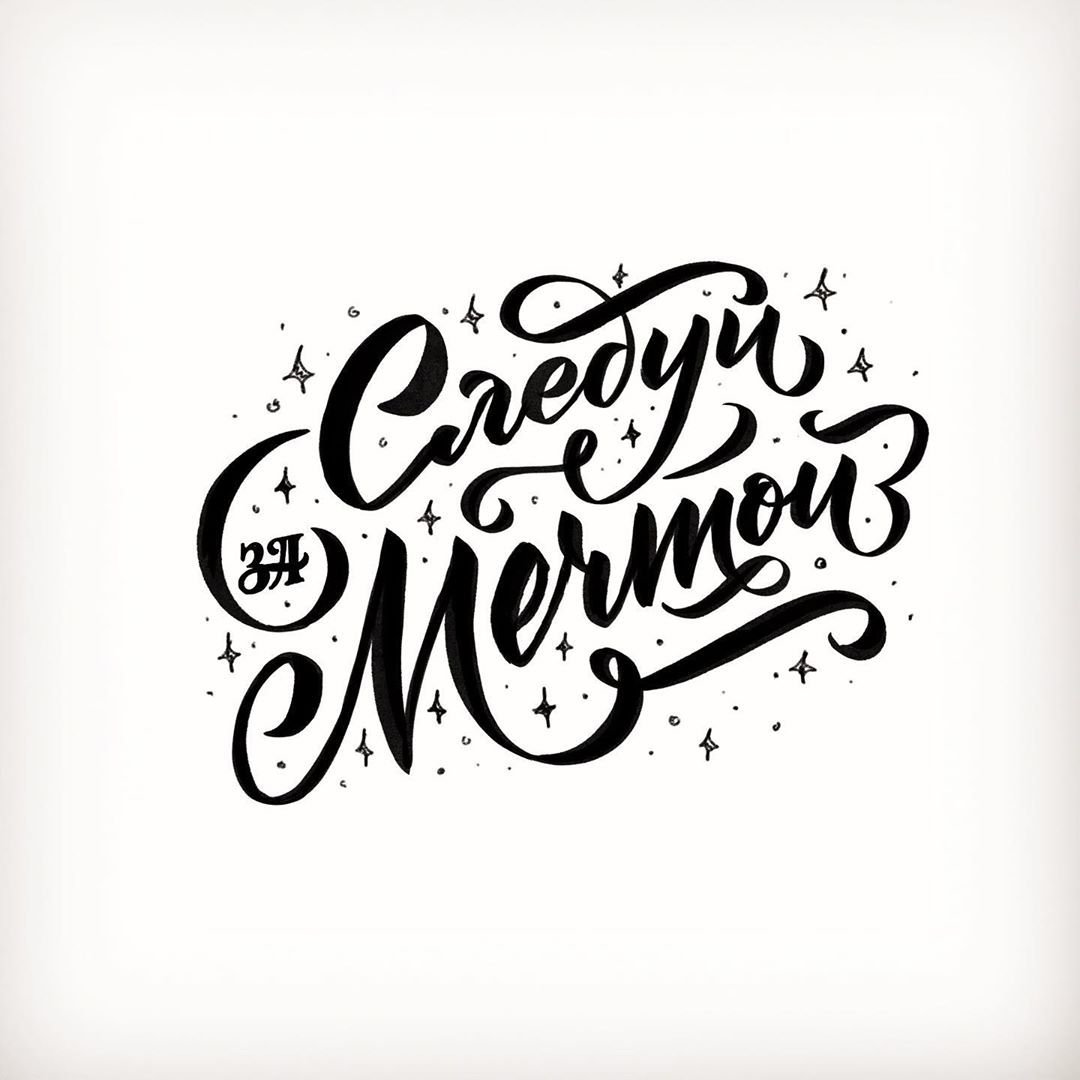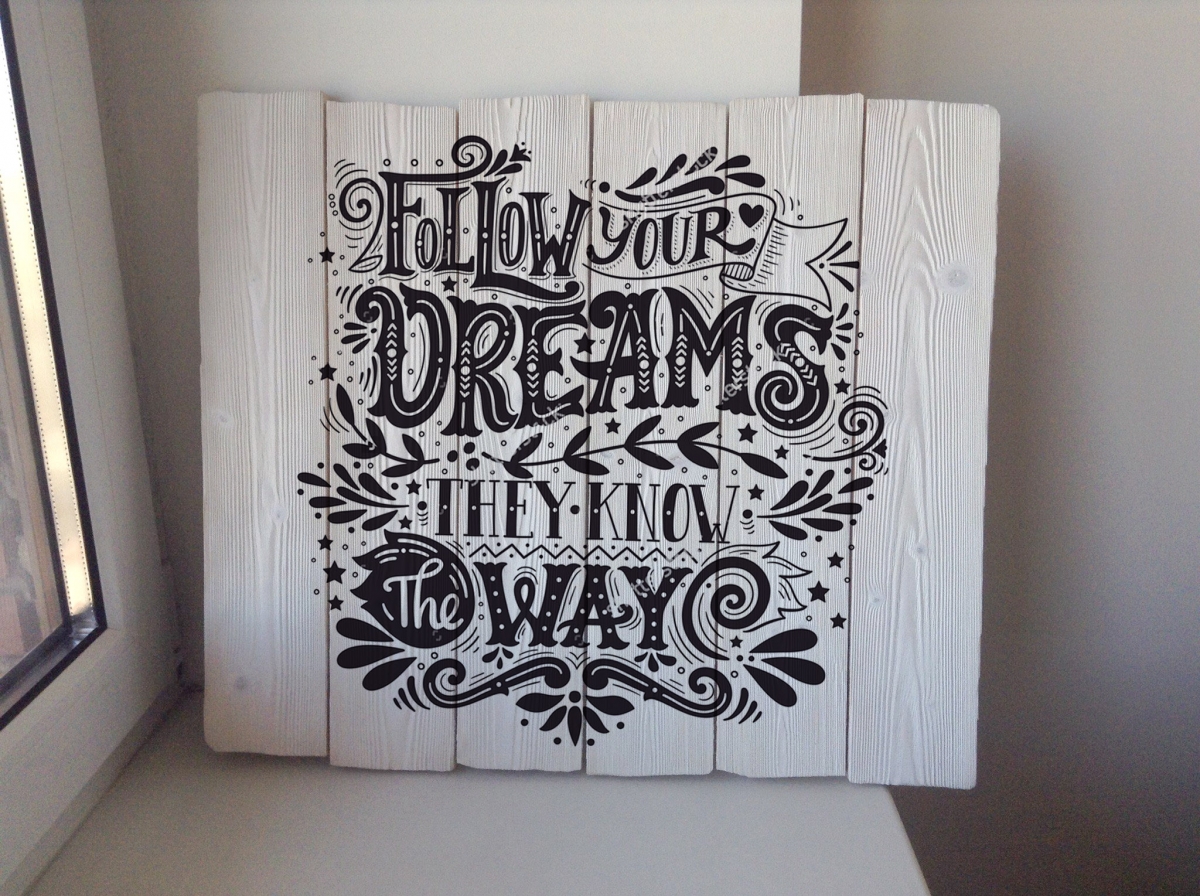
Продолжая тему предыдущей публикации, хотелось бы заметить, что вопреки растущей популярности всевозможных гаджетов, интерес к ручному письму совсем не угас.
Примером этого может служить каллиграфия
и леттеринг, которые завоевывают симпатии все большего количества
людей. Так, что же обозначают эти понятия?| Matt Vergotis: https://dribbble.com/shots/1417259-Beautiful |
Каллиграфия – одна из отраслей изобразительного искусства или искусство красивого письма. Современная каллиграфия довольно разнообразна — от бытовых рукописных надписей на открытках до высокого искусства, в котором экспрессия написанного рукой знака не всегда рождает чёткие буквенные формы. Классическая каллиграфия значительно отличается от шрифтовых работ и нестандартных рукописных форм.
Сейчас каллиграфия существует в форме пригласительных открыток и свадебных поздравлений, а также в граффити, шрифтах и рукописных логотипах, в религиозном искусстве, графическом дизайне, в высеченных надписях на камнях и в исторических документах.
Каллиграфию используют
в качестве оформления на телевидении и в сети Интернет, в различных
характеристиках, свидетельствах о рождении и в других документах, где
предполагается писать от руки. Приёмы каллиграфии очень
разнообразны. Могут использоваться завитки, лишние хвостики, крючки,
попеременно твёрдые и мягкие штрихи, плавные и ломаные линии, угловатость,
вписывание букв или слов в геометрические фигуры или определённое пространство,
вычерчивание одних букв и оставление невычерченными других, расположение букв
или слов в виде определённых фигур (арабская каллиграфия), рамки, вычерчивание
букв двойным или тройным слоем, проведение параллельно уже проведённым линиям
линий иного цвета и другие. Минимальный набор для письма
состоит из бумаги, пера и туши. Также для каллиграфии могут быть использованы
авторучка с пастой различных цветов, акварель, гуашь, чернила, баллончик с
краской (для граффити), пастель, уголь, маркеры, брашпены и многое другое. Каллиграфия так же развивает
мелкую моторику – совокупность скоординированных действий нервной, мышечной и
костной систем, часто в сочетании со зрительной системой в выполнении мелких и
точных движений кистями и пальцами рук и ног.Леттеринг – это графическое начертание букв и знаков, составляющих единую стилистическую и композиционную систему.
Мастер может выступать в качестве художника и изобретать новые шрифты в соответствии со стилем разрабатываемого проекта.
В отличие от каллиграфии, леттеринг больше похож на изобразительное искусство, главный объект которого — буквы. Стилистика леттеринга зависит только от вашей фантазии. В качестве материалов можно использовать те же инструменты, что и для каллиграфии. В последнее время леттеринг все чаще можно встретить в кафе (оформление меню и спецпредложений), на афишах и открытках, в оформлении книжных обложек, рекламных объявлений и т.
д. Всем этим занимаются люди, владеющие искусством
леттеринга. Научиться ему несложно, главное – ваше желание и чуть-чуть